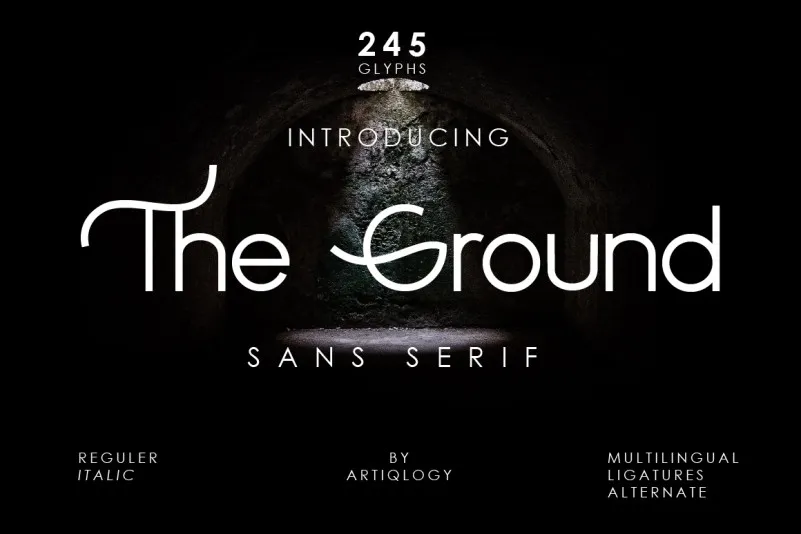
A font ‘The Ground’ é uma opção ideal para aqueles que buscam uma tipografia contemporânea e elegante para seu próximo projeto visual. Inspirada na família de tipo sans, esta font possui um formato único dos caracteres maiúsculos que lhe adiciona uma dose extra de modernidade e sofisticação aos seus projetos, tornando-os imediatamente visíveis e chamativos. Perfeita tanto para logomarcas luxuosas quanto para títulos de livros ou filmes, ‘The Ground’ também se adapta perfeitamente ao design de marcas de moda, capas de revistas, gráficos publicitários em roupas, desenhos artísticos, citações e muito mais. Esta font é uma ótima escolha para quem busca criar ambientes digitais e físicos modernos e sofisticados. Além disso, sua versatilidade faz dela uma opção confiável para designers que buscam dar um toque final diferenciado a seus projetos. Com ‘The Ground’, você pode adicionar um padrão de design único ao seu trabalho, mantendo sempre o foco em criar algo inovador e atrativo.